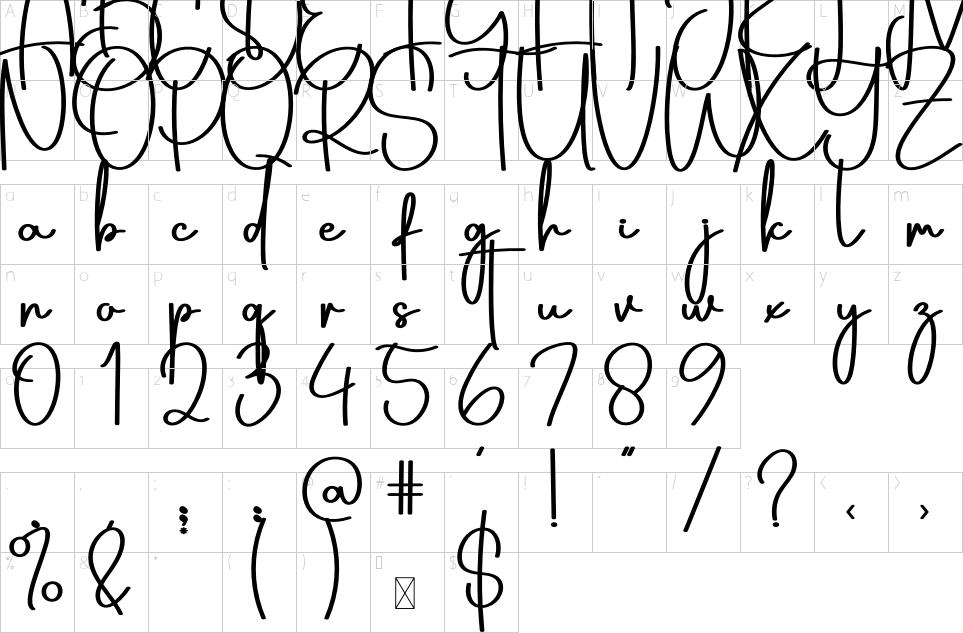
A Getting You é uma elegante fonte que traz uma sensação natural e envolvente para qualquer projeto gráfico ou tipografia. Ela foi projetada por scratchones, cujas linhas suaves e harmoniosas se destacam por seu equilíbrio entre modernidade e sofisticação. Esta font é perfeitamente adaptável tanto para aplicações Windows quanto Mac, o que a torna uma opção versátil para designers de todos os níveis. Com apenas 539 downloads desde sua disponibilização, Getting You não só se destaca pela sua beleza visual, mas também por seu design único e intuitivo, oferecendo aos usuários um recurso gráfico gratuito que merece ser explorado. Seja para aplicativos de produção editorial ou simplesmente como um elemento estético em projetos pessoais, a Getting You font é uma escolha inteligente para aqueles buscando um estilo sofisticado e envolvente.